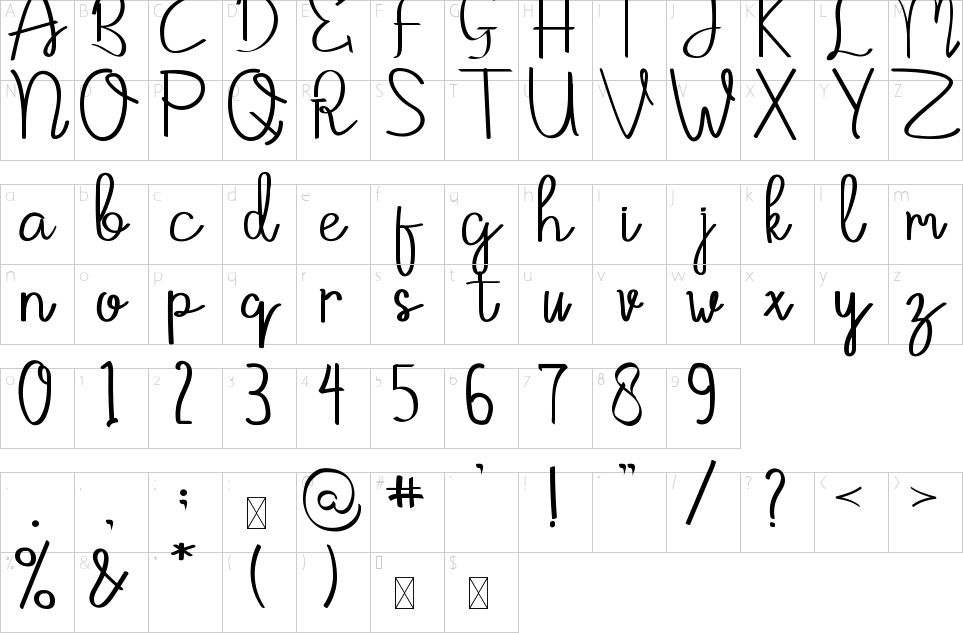
Descubra a sofistica e a elegância da Anyta font, uma grata adição para seus projetos digitais. Criada pelo InermediaSTUDIO, Anyta oferece um estilo moderno e versátil, perfeito para textos de negócios e design gráfico. Com downloads de 255 vezes, essa fonte se destaca pela sua facilidade de uso e simplicidade, tornando-a uma ótima escolha para designers que buscam uma fonte confiável e estilosa. Seja para criação de materiais de marketing, design de sites ou simplesmente para dar um toque especial a seus documentos, a Anyta font é uma escolha inteligente. Descubra mais e aproveite esta fonte gratuita para seu próximo projeto.